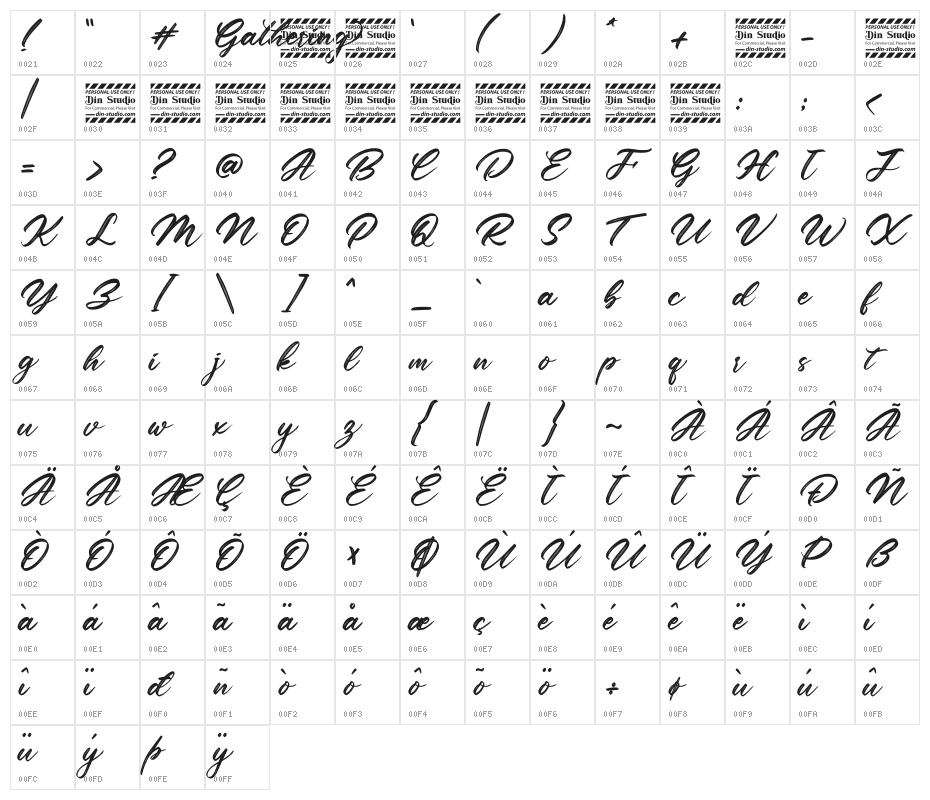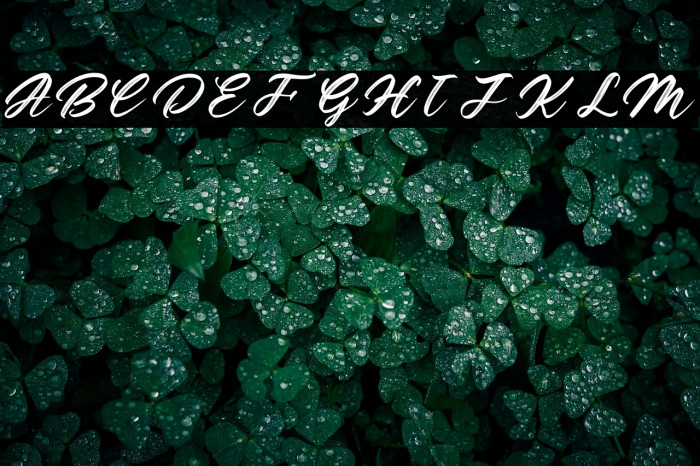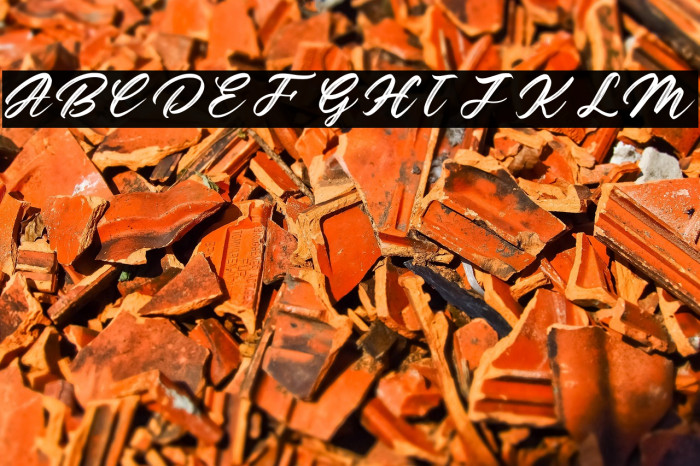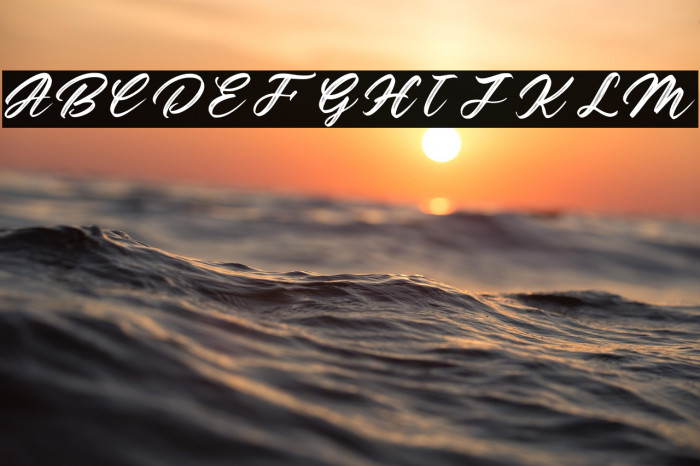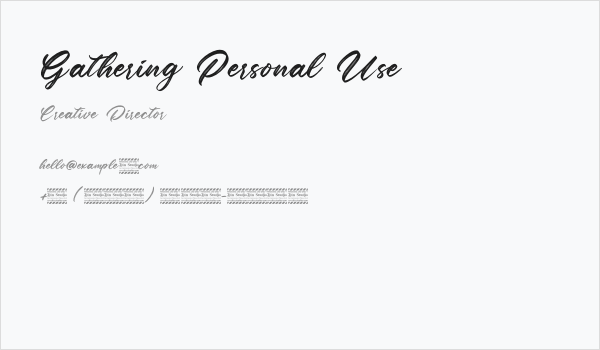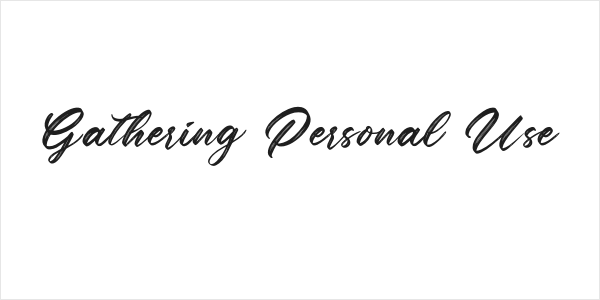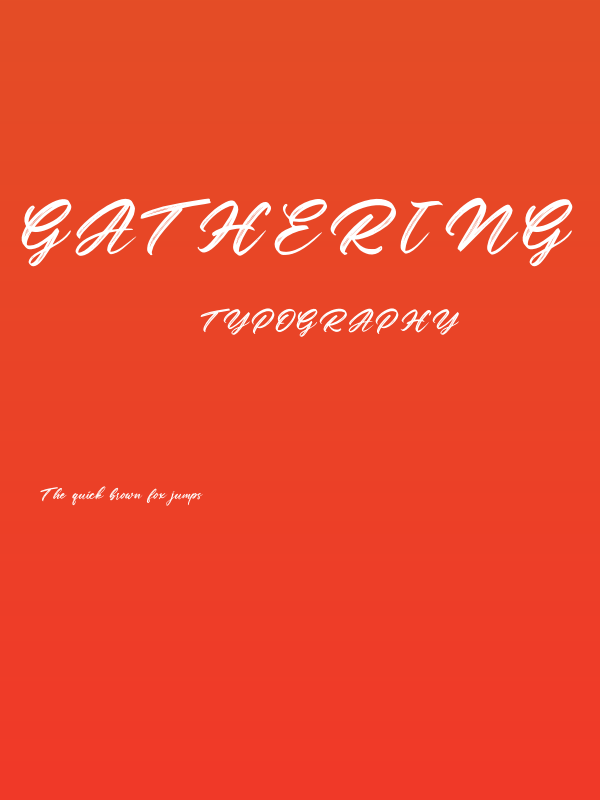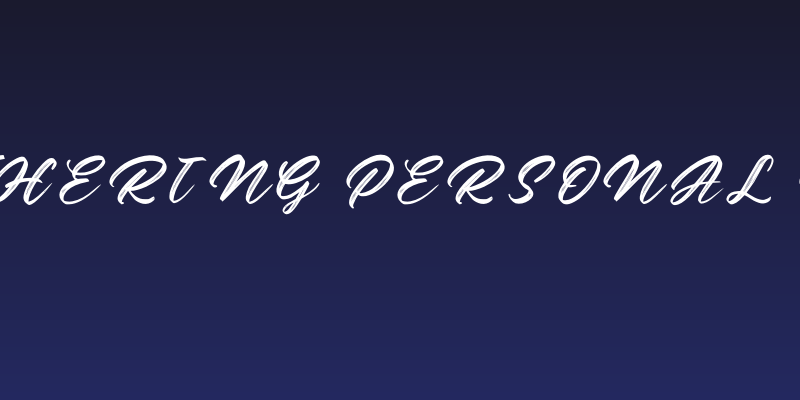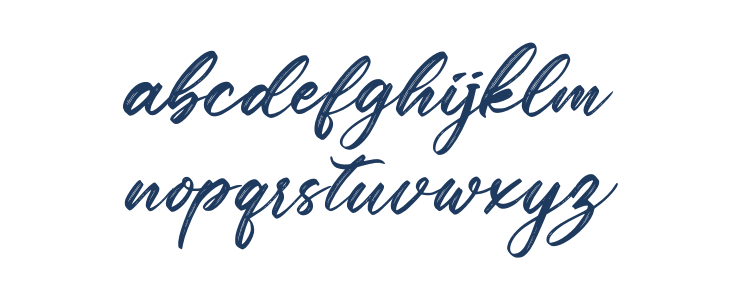
Gathering Personal Use Font
| Stile generale | Modern, Decorative |
| Caso d'uso | Logos, Headlines, Invitations |
| Progetti proposti | Ideal for wedding invitations, branding, logo design, and social media graphics where a touch of elegance and personality is desired. |